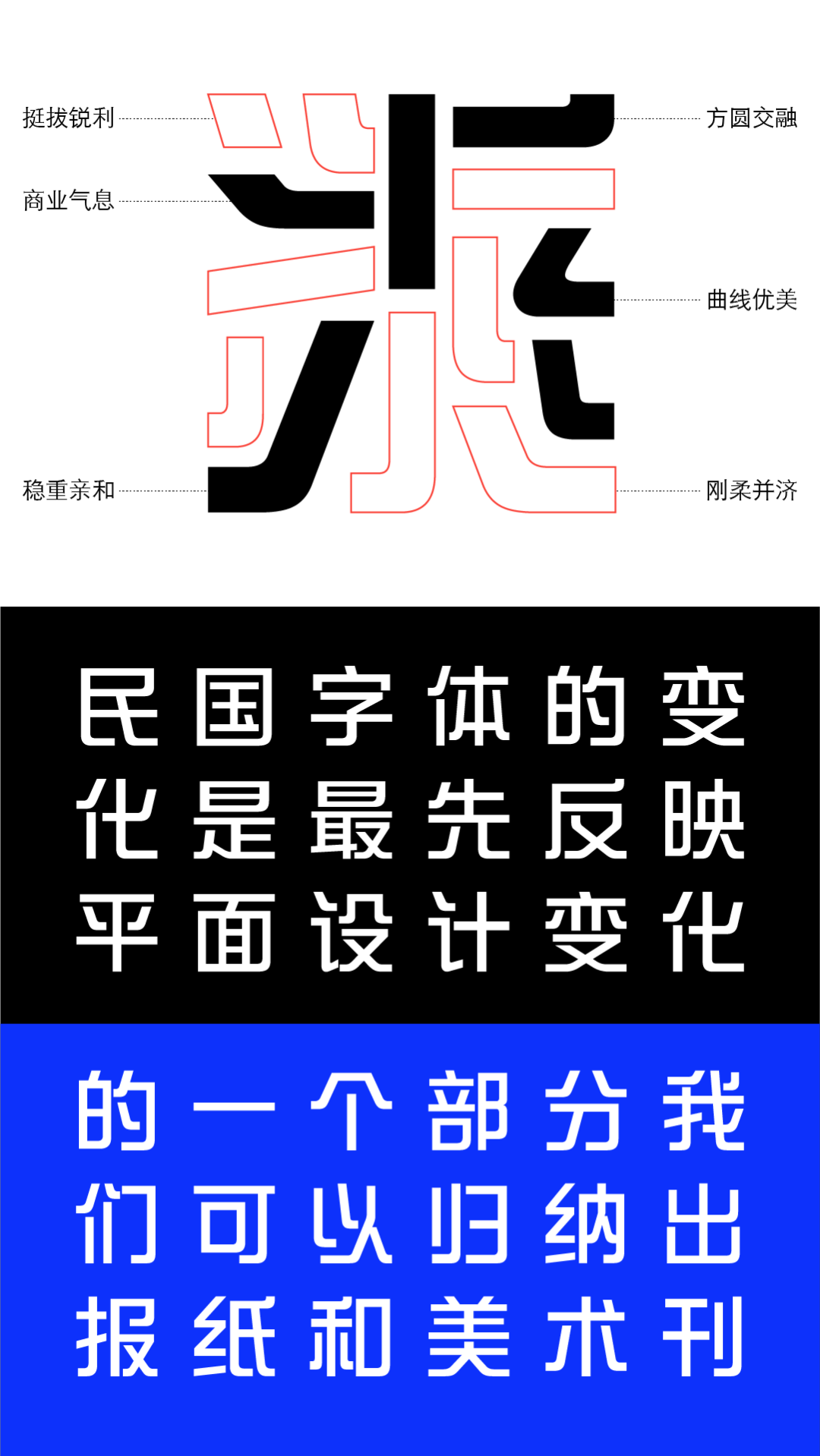
方正新综艺黑家族
综艺体由郭炳权老师创作于上世纪70年代,与英文字体“Helvetica”有异曲同工之妙,至今仍受大众所喜欢,新综艺黑沿用综艺体部分特征,结合更舒适的视觉效果对相关笔画进行了再度的修改使其整体感觉更加的舒畅灵动,整体字形端正平稳,结构简洁大方,新综艺黑共有11个字重,更加的适合运用于各类场合及品牌宣传推广,是一款实用的字体。
对于文字和字体设计来说,通常有两个主要服务对象:一个是满足人们日常排版、阅读需求的文字信息出版行业;
另一个则是商业市场环境下,为品牌及其产品进行宣传的广告行业。
观察中国文字和字体设计的演变历史,我们发现,早在民国时期的各种报纸杂志中,就会通过字体的差异性设计来让广告、标志更加醒目,从而达到显著而广泛的产品宣传效果;
从1930年起,在商业社会对于刺激消费的专业化需求下,图案型文字和美术字的创作水平和使用频率更是达到了顶峰。
民国美术字风格海报
进入现代社会,商业文化的繁荣为字体设计的丰富提供了物质基础,利用醒目的装饰性美术字实现商业宣传的目的,这一传统也在汉字文化圈得到很好的继承和发展。
这其中的代表人物,首推字体设计师郭炳权。
郭炳权的创字故事
郭炳权的字体设计,与他长时间服务于商业文化广告公司的职业背景有很大关系,风格延续了民国以来强调商业、实用的美术字传统,设计上强调视觉的说服性和震撼效果。
他的重要代表作之一,便是开启现代美术字中文字库先河的“综艺体”。
郭炳权于60年代创作的综艺体手稿
当时,以瑞士字体设计师爱德华德·霍夫曼(Eduard Hoffmann)和马克斯·米耶丁格(Max Miedinger)设计的传奇无衬线字体Helvetica 在商业中的应用最为广泛,体现了现代设计对更加中性的无衬线字体的需求。
郭炳权充分吸收Helvetica 明晰、中性、极具条理性的字体特征,并结合民国时期图案型文字及美术字的设计手法,完成了综艺体的设计。
综艺体最粗与最细两款(可左右滑动查看)
综艺体的诞生,是近代中国美术字设计传统与西方现代设计理念的一次重要结合。汉字字体形态的高度几何化处理,使其具有鲜明的视觉特征,既现代又时尚,辨识度极其高。
综艺体在华人世界非常受欢迎,无论是杂志报刊、商业广告,还是街头店招,都能看到它的身影。
方正综艺体
方正综艺体字稿
方正综艺体的几何特征鲜明,字形轮廓几乎贴近整个字面框,中宫宽松,结构饱满,重心平稳;笔画较粗,撇、捺笔画呈镜像对称,拐弯处较为圆润。
方正综艺体
方正新综艺黑
为了更加广泛地满足商业广告用字的需求,郭炳权在原综艺体的基础上对字体的笔画、结构进行了全面的升级改造,打造出更加精致耐用、简洁大方的方正新综艺黑,
让这款经典字体在走过近五十年韶光岁月之后,在新时代焕发出新的光彩。
新综艺黑沿袭了综艺体对Helvetica 字体风格的借鉴,在字体部件的设计上,保留了几何化的设计手法,笔画多以直线的形式呈现,仅在撇捺末端及一些折笔处作了圆弧转角的处理。
方正新综艺黑设计手稿
方正新综艺黑借鉴了Helvetica的笔形风格
新综艺黑沿用了综艺体部分笔形特征,对字体的重心、布白及部分笔画细节进行了再度修改。
精细化调整后的新综艺黑字形端正、重心平稳,结构简洁大方,保留了美术字常用的对称设计手法,具有镜像对称的特殊美感。
方正新综艺黑是一款包含11个字重的家族字体,丰富的字重变化搭配标准的西文字母设计,使其成为一款风格稳重、严谨的百搭字体,
可广泛应用于电视媒体、报刊杂志、航空物流、街头店招、品牌广告、书籍包装、海报设计等各种不同宣传媒介的标题应用。